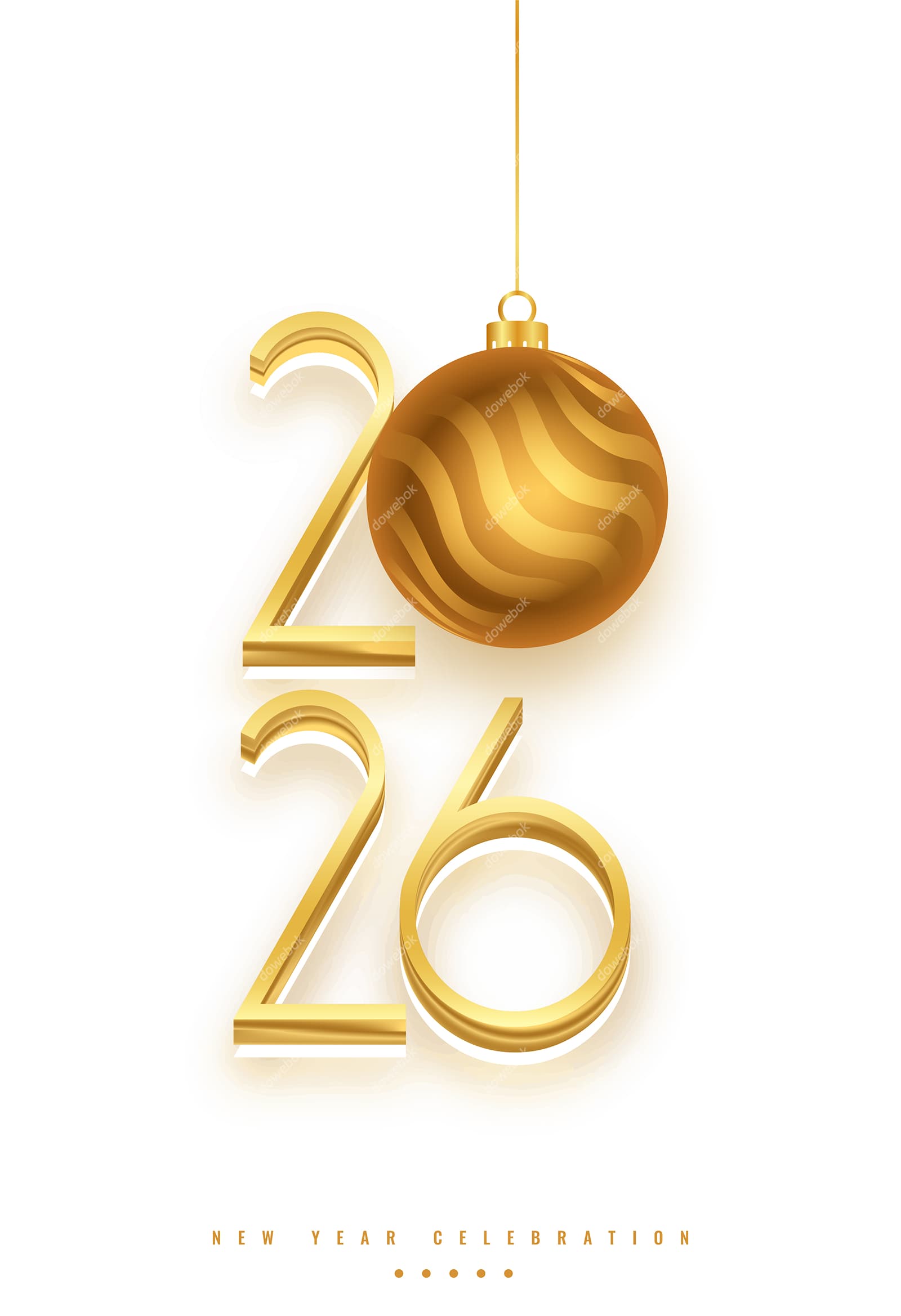
这是一款金纹装饰球和立体数字设计的 2026 新年快乐海报矢量素材,白底衬出金色系元素,立体 “2026” 字体以镂空 + 金边设计呈现,质感精致轻盈;旁侧悬着金线牵引的金纹装饰球,底部配 “NEW YEAR CELEBRATION” 字样。整体全金配色奢华统一,装饰球与镂空字体结合,既显新年的雅致喜庆,又以简洁设计传递出高级感,适配贺卡、装饰物料等场景。